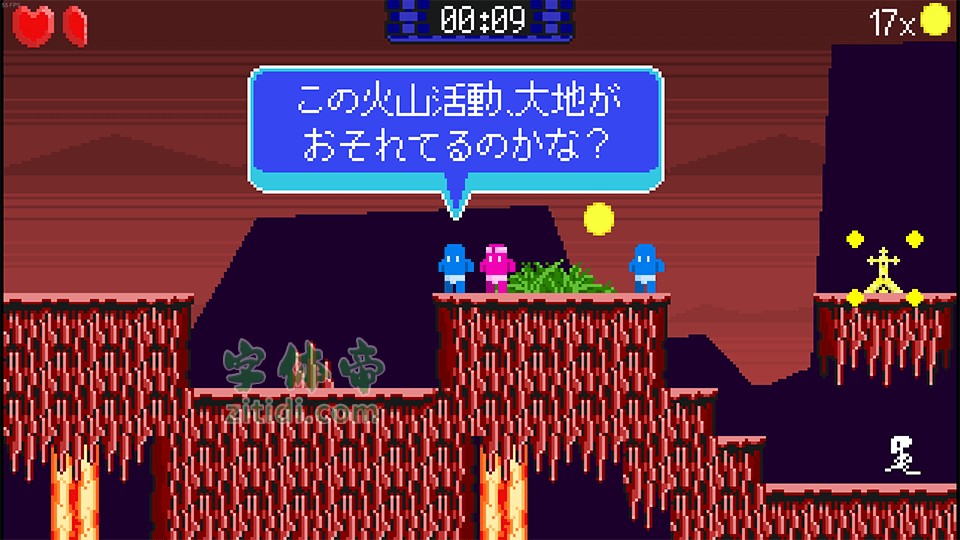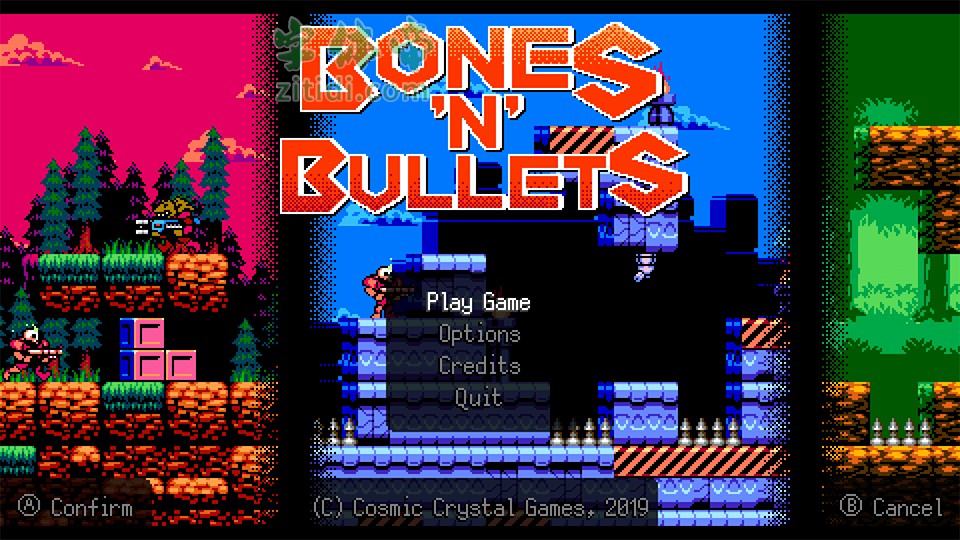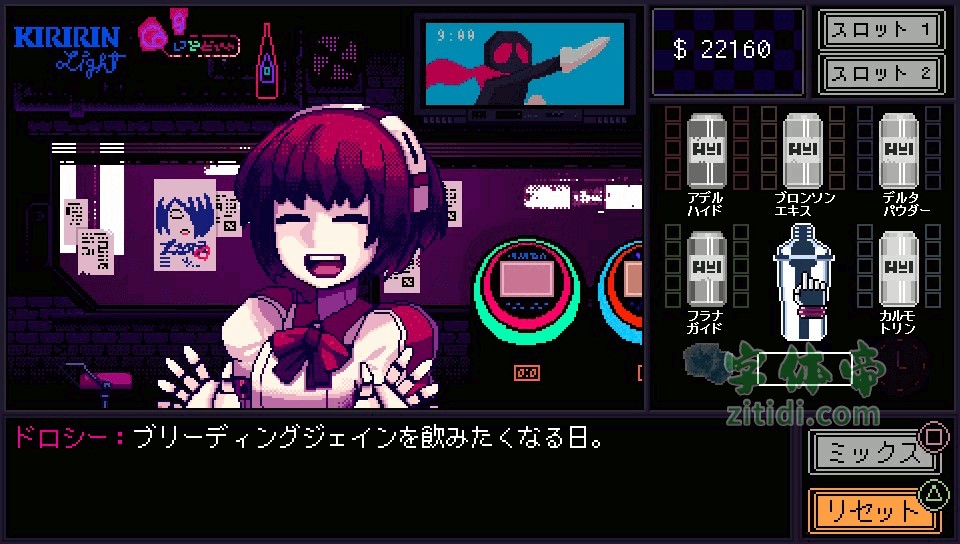
像素Silver是一款主要用于游戏项目的像素字体,Silver在字体中内置了TRC和Lotcheck兼容的gamepad按钮,还有完整的键盘和鼠标提示!这是一个正在进行的项目,将不断更新新的Unicode字形。其目标是成为像素游戏和应用程序的实际字体。
“Silver像素体”是一款书写很新颖的字体,字体大方,适合各种设计作品使用!欢迎下载!